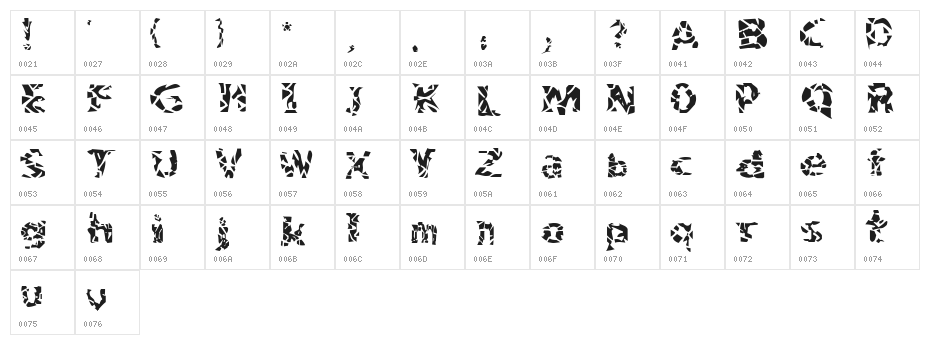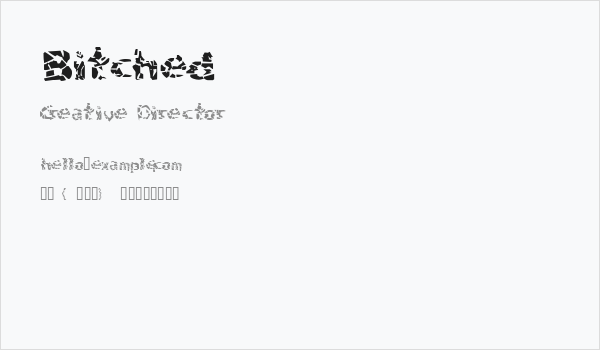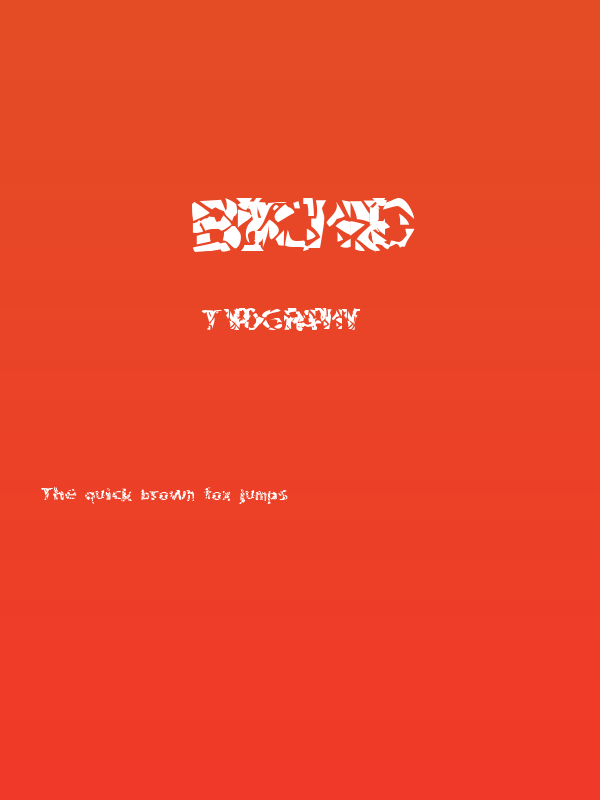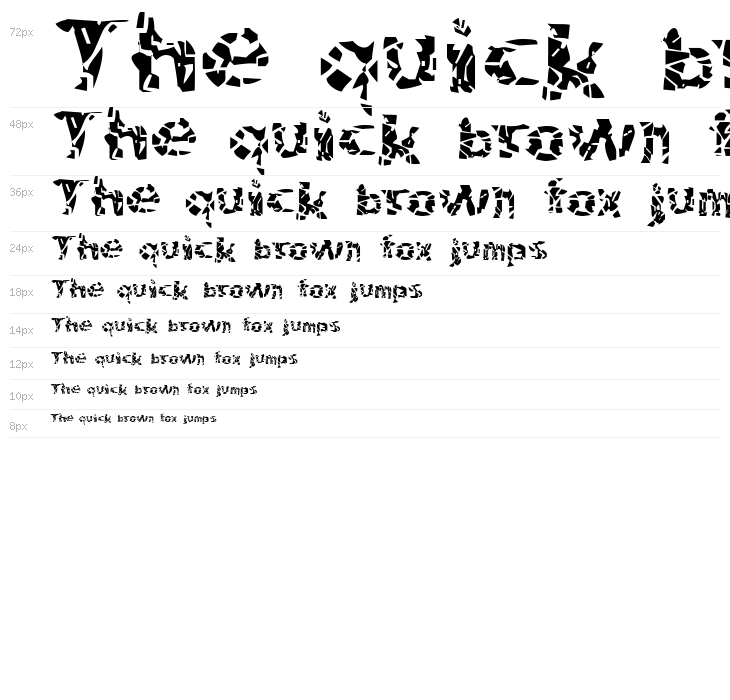
Bitched Font
| श्रेणियाँ | Dotted |
| कंट्रास्ट | High |
| समग्र शैली | Modern, Decorative |
| उपयोग का मामला | Logos, Headlines, Artistic designs |
| सुझाए गए प्रोजेक्ट | Ideal for album covers, edgy posters, modern art projects, and any design requiring a bold, artistic statement. |